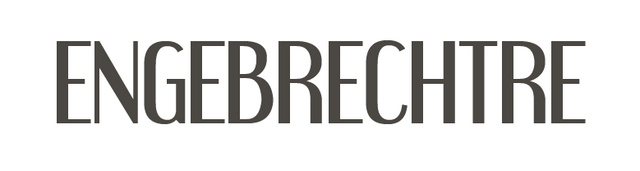
Schreibschrift gesucht
Ich bin auf der Suche nach einer Schreibschrift, die gut mit der Engebrechtre
Regular harmoniert, nicht zu schnörkelig und gut lesbar ist.
Hier die Engebrechtre als Beispiel:
und noch einige Beispiele, was ich mir vorstellen könnte:
Die Schrift sollte zeitlos sein, nicht zu verspielt oder zu schnörkelig,
sie soll nur die Engebrechtre etwas auflockern.